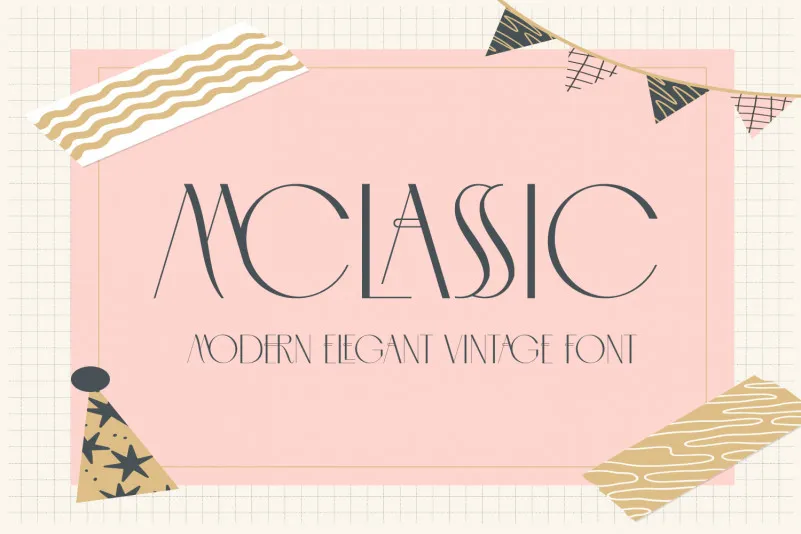
MCLASSIC FONT é uma elegante fonte sans-serif inspirada nos marcos de luxo do mundo da moda. Inspiradora e moderna, ela se destaca tanto nas configurações do texto quanto nos tamanhos maiores para exibição, tornando-a perfeita para uso em logos, headlines e até mesmo embalagens. Este font oferece duas opções: REGULAR e ITALIC. Suas linhas limpas e minimalistas criam um ambiente de sofisticação que se adapta bem a diversos usos, como logotipos, cabeçalhos para anúncios e embalagens. MCLASSIC FONT é uma escolha inteligente para qualquer projeto visando um toque moderno e elegante. Foi projetada pela 177Studio.